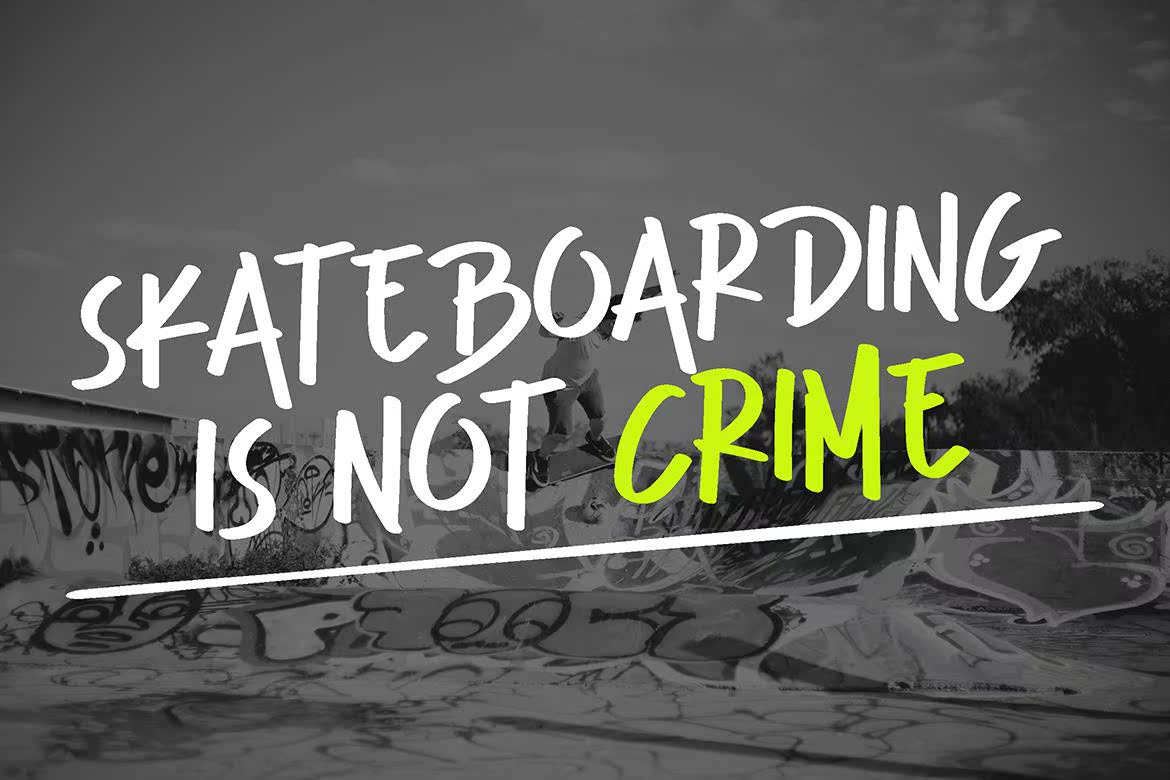
ClintMarker–RebelUrbanFont来自城市精神和可信的青少年签名Font。无忧无虑,永远停留在爱尔兰的边缘。ClintMarker将制作您所写的一切,无限制能量祝福。ClintMarker–RebelUrbanFont来自城市精神和可信的青少年管理者签名。无忧无虑,永远停留在爱尔兰的边缘。ClintMarker会让你所写的一切都无限制能量祝福。